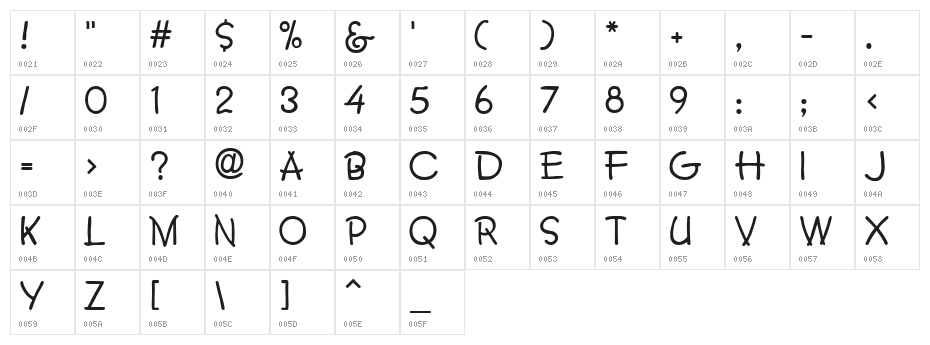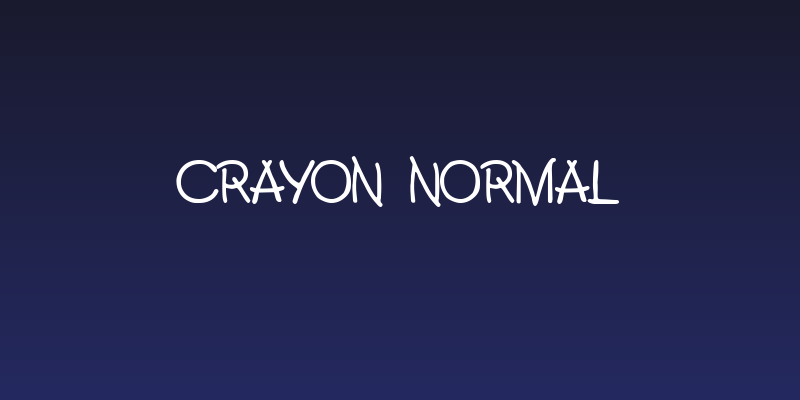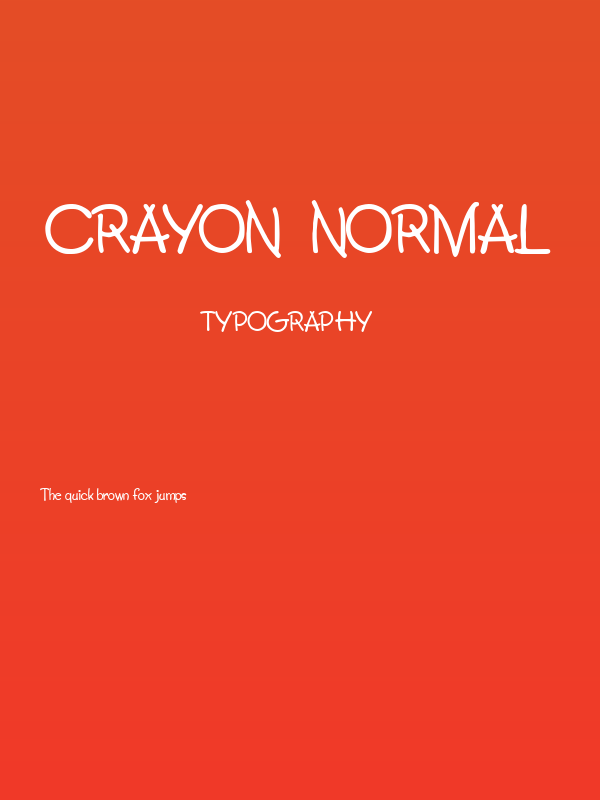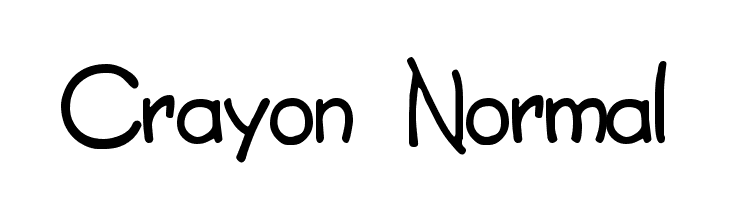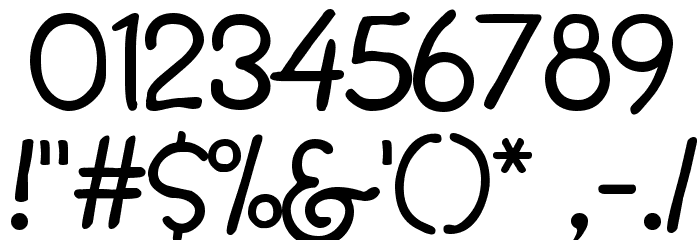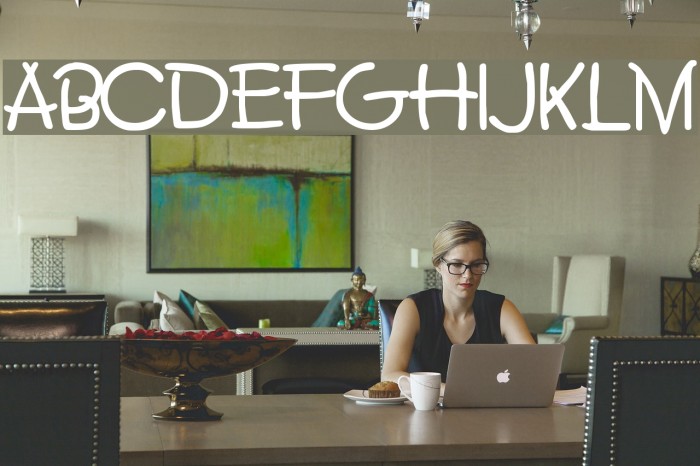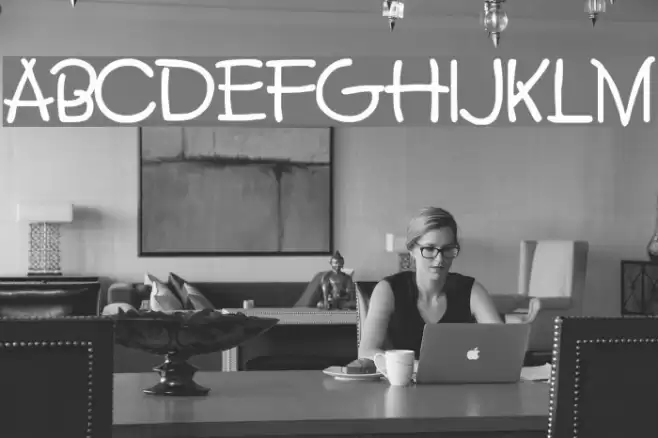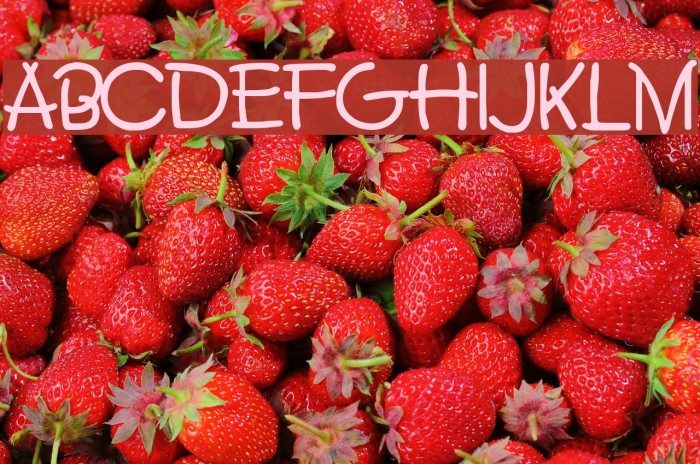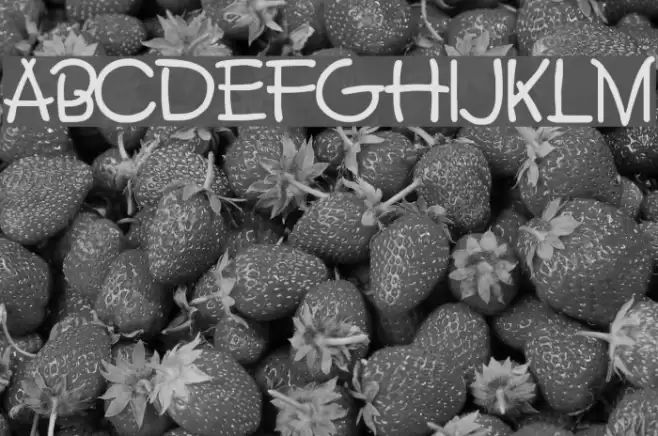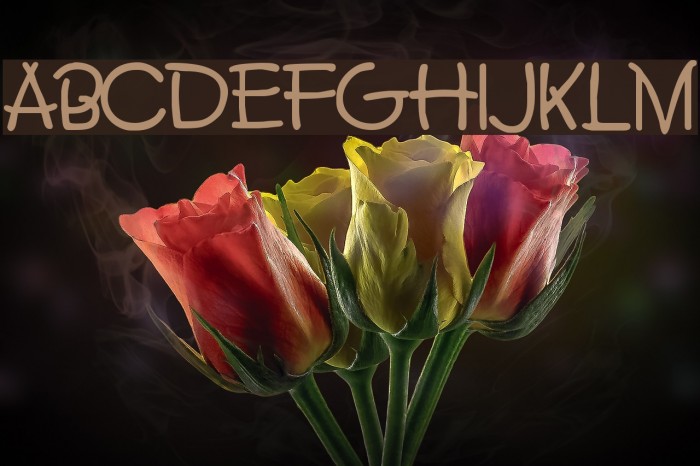
Crayon Normal Font
| Gesamtstil | Playful |
| Anwendungsfall | Headlines, Logos, Creative projects |
| Vorgeschlagene Projekte | Ideal for children's books, educational materials, playful branding, and creative art projects. |